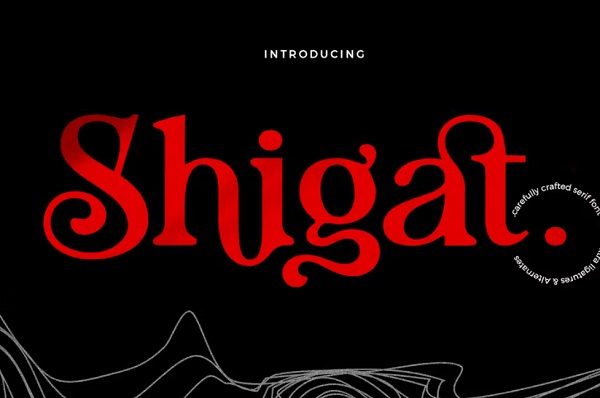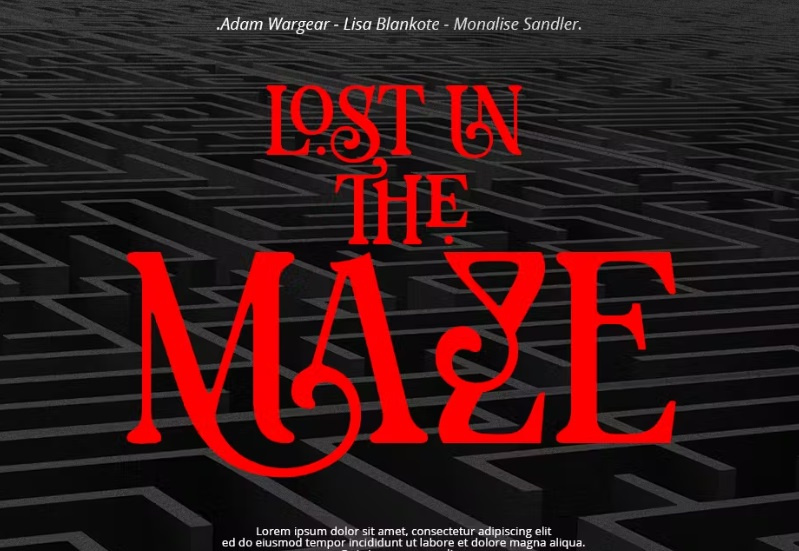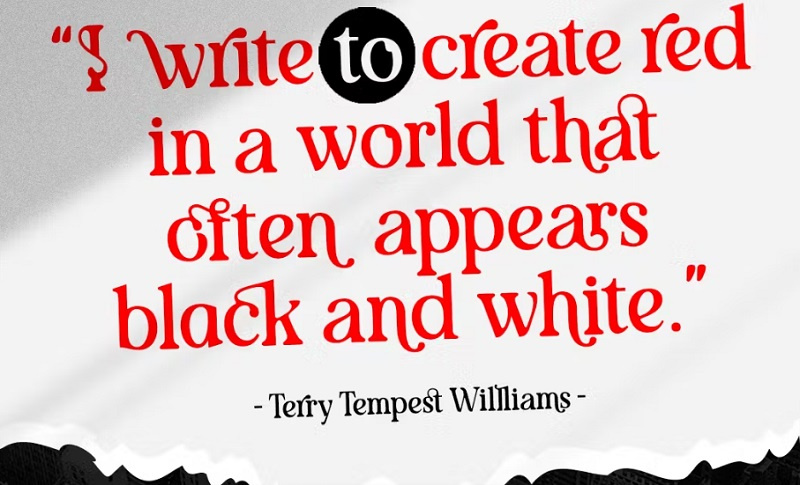
دانلود فونت انگلیسی Shigat
دانلود فونت انگلیسی Shigat از جی اف ایکس دانلود. یک فونت زیبا با طراحی منحصر به فرد و مدرن که می توانید برای امور مختلف از آنها استفاده کنید. این فونت انگلیسی مناسب برای انواع پروژه ها و طراحی ها از جمله لوگو ها، کارت ، طرح بندی مجلات، دعوت نامه ها، سرصفحه ها و غیره می باشد.
ویژگی های فونت انگلیسی Shigat از جی اف ایکس دانلود
✅ نام فونت انگلیسی: Shigat
✅ شامل حروف اصلی لاتین
✅ حروف بزرگ و کوچک
✅ اعداد و نقطه گذاری
✅ پشتیبانی چند زبانه